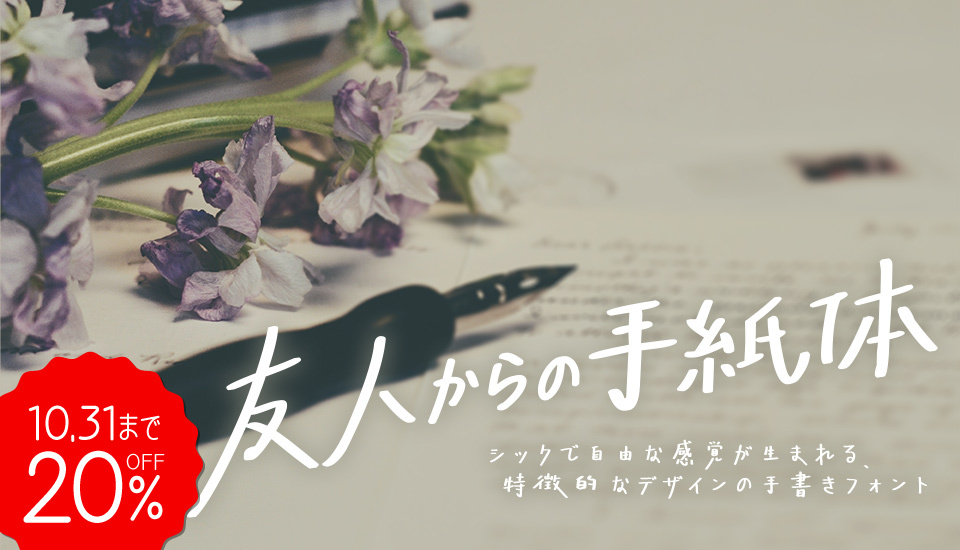
楽フォント 友人からの手紙体
『フォントを通して繋がるすべての人が気楽に楽しめるように、文化の多元的要素を含むフォントの創作で、文字による彩りを日常にもたらす』を理念に掲げる楽フォントから、2024年にリリースされた「友人からの手紙体(ゆうじんからのてがみたい)」。
「友人からの手紙体」は、全体的に特徴的なデザインが施された手書きフォント。一部の筆画が下向きに引き伸ばされ、シックで自由な感覚が生まれます。文字は強い視覚的表現を持ち、雑誌や書籍、芸術作品、パーソナル・ブランディングだけでなく、柔軟なライセンスで印刷物からWebコンテンツ、ゲーム・アプリ、映像まで幅広く活用いただけます。
友人からの手紙体の特徴
一部の筆画が下向きに引き伸ばされた、躍動感のある手書きフォント
一部の筆画が下向きに引き伸ばされることで、シックで自由な感覚が生まれます。
文字が視覚的に強く印象に残るデザイン
個性的でありながらも、スッキリとした字形で高い視認性を持つデザイン。
おすすめの使い方